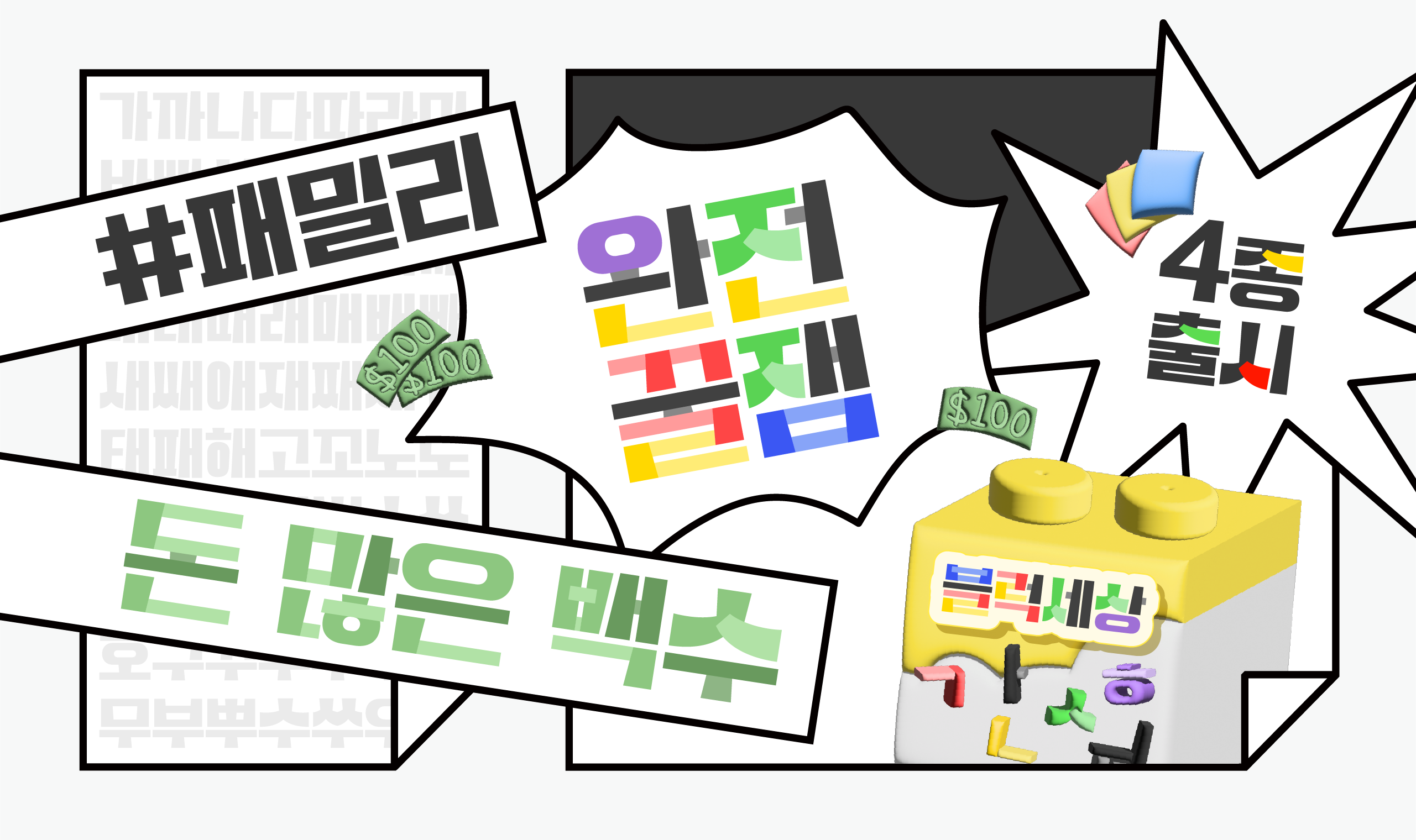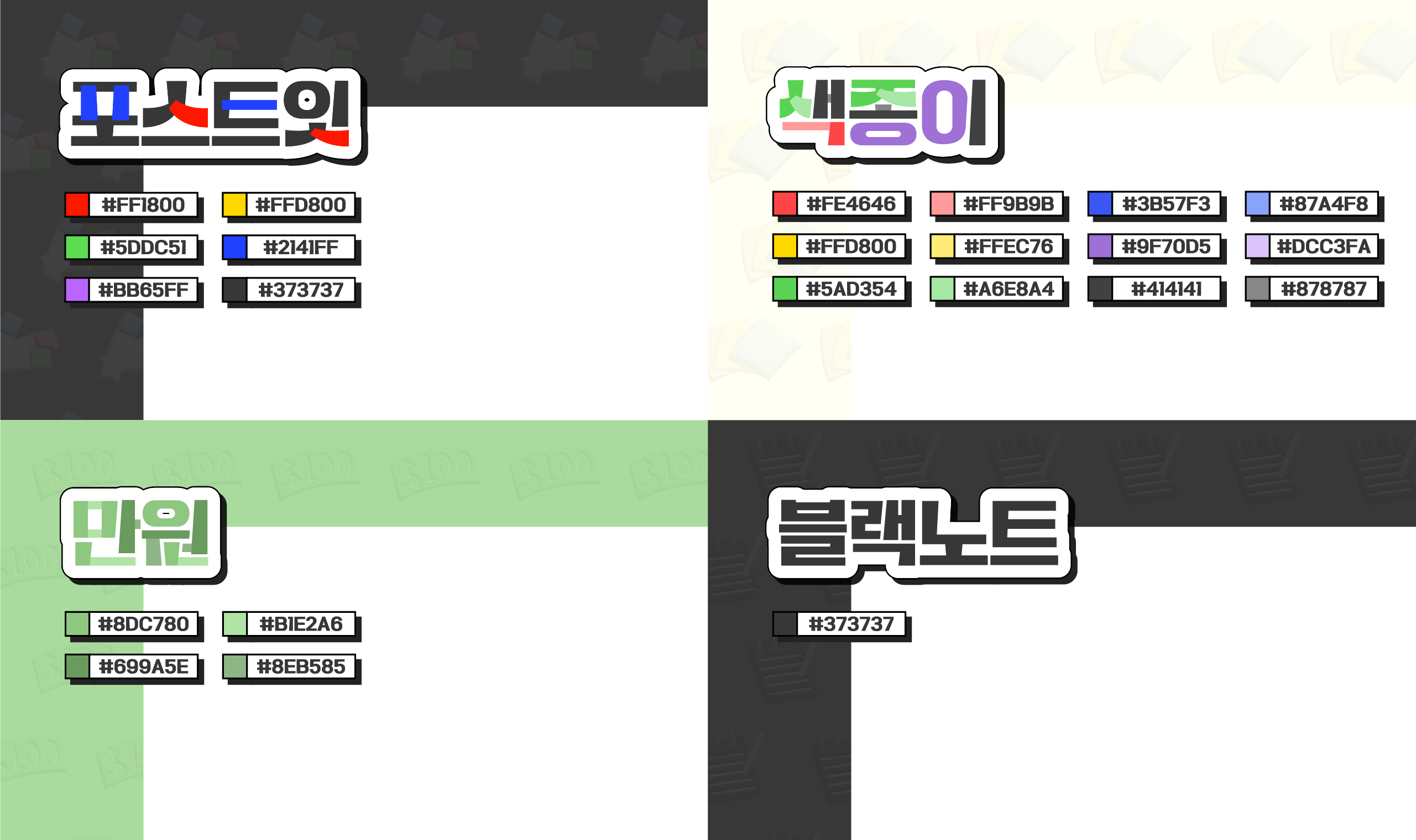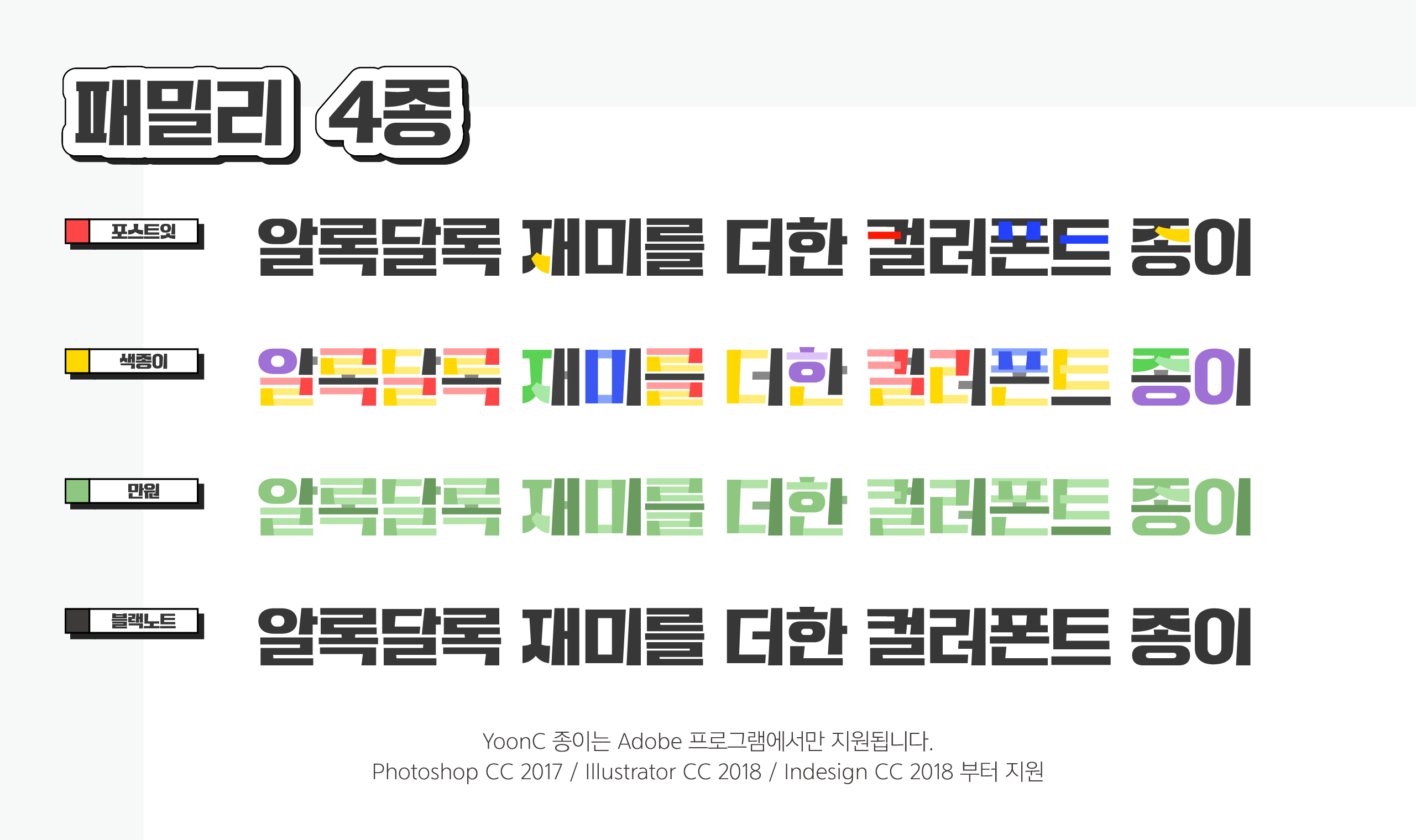
컬러폰트 '종이'는 만원 지폐와 색종이처럼 컬러풀한 색상을 지니고 있는 다양한 종이들을 글자로 표현한 제목용 서체입니다. 부채꼴의 형태를 한글에 더해 종이가 말리는 느낌을 주어 자유로운 분위기를 연상시키고, 가로획과 세로획의 굵기 대비를 통해 무거운 느낌은 해소시켜 포스터나 방송 타이틀과 자막 등 강조가 필요한 곳에 포인트 서체로 활용하는 것을 추천합니다.(컬러폰트란 색을 따로 지정하지 않아도 폰트 파일 자체가 색상을 포함하고 있는 폰트입니다.)
YoonC 종이